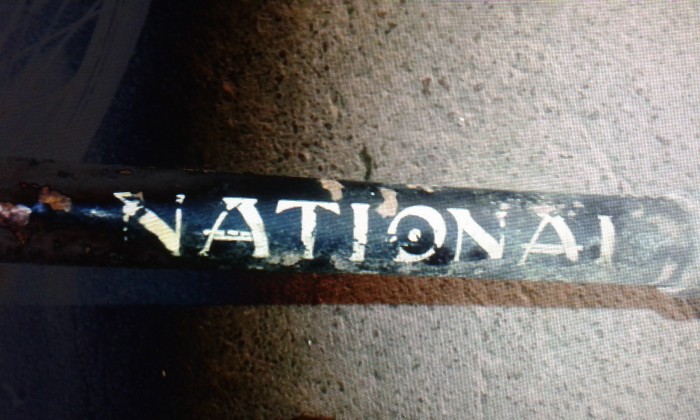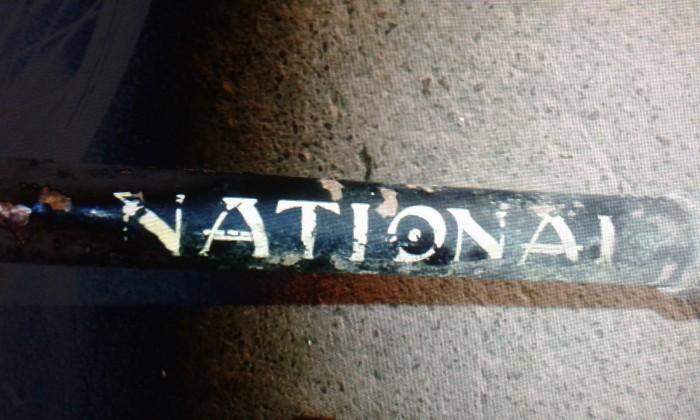
NATIONAL Fahrrad Hainsberg
Hallo,ich suche die Schriftart/ den Schriftzug für eine Fahrradrestauration eines Herrenrades (Baujahr um 1950) der Hainsberger Fahrradwerke Dresden-Freital.
Die Fahrradmarke heißt NATIONAL (sorry,hieß eben so) ,wie auf dem Bild zu sehen.
Wär schön ,wenn ich etwas vergleichbares finde.
Tja, National heißt es, weil die Firma schon zu einer Zeit existierte, als National eben sehr angesagt war.
Das Logo auf deinem Rahmen kommt aber leider aus einer Zeit, als Logos i.d.R. noch komplett von Hand gezeichnet wurden, und seltenst dafür eine Satzschrift verwendet wurde.
wie catfonts schon sagt, dass logo basiert nicht auf einer satzschrift, sondern ist mit großer wahrscheinlichkeit von hand gezeichnet. ich würde es ordentlich abfotografieren und mit der vorlage zu einem grafiker gehen, der kann dir das sicherlich nachbauen, denn die wichtigsten bestandteile sind ja vorhanden.